大正タイポグラフィ
藤原太一編著「図案化せる実用文字」(大正十四年発行)、「絵を配した図案文字」(大正十五年発行)の新装合本復刻「大正タイポグラフィ」がマール社から2019年3月20日に発売される。
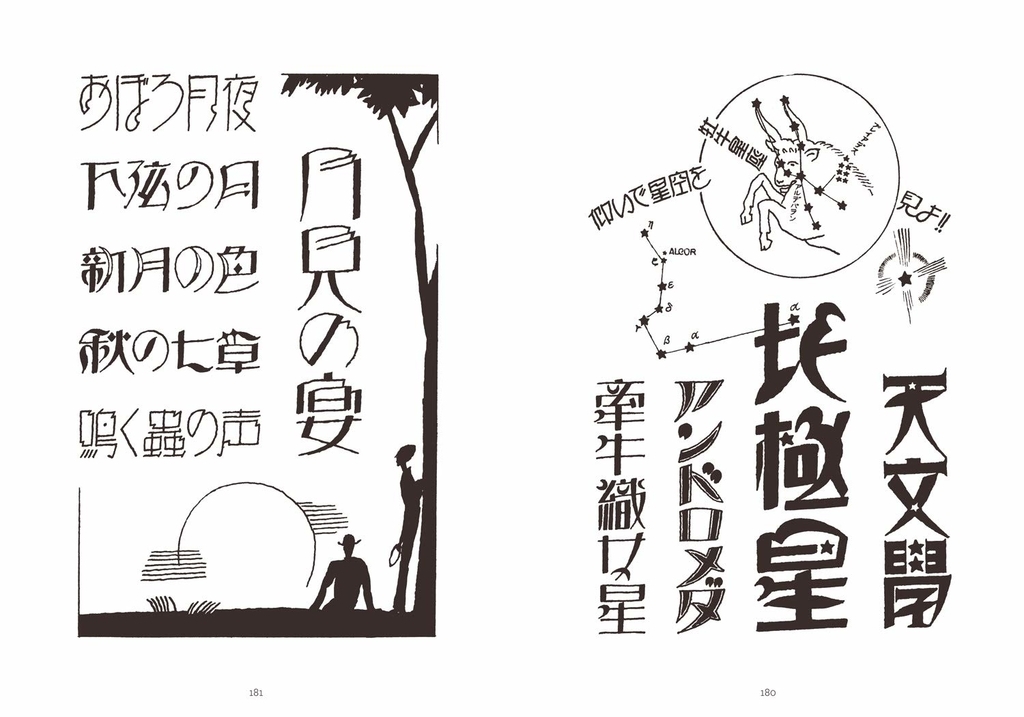
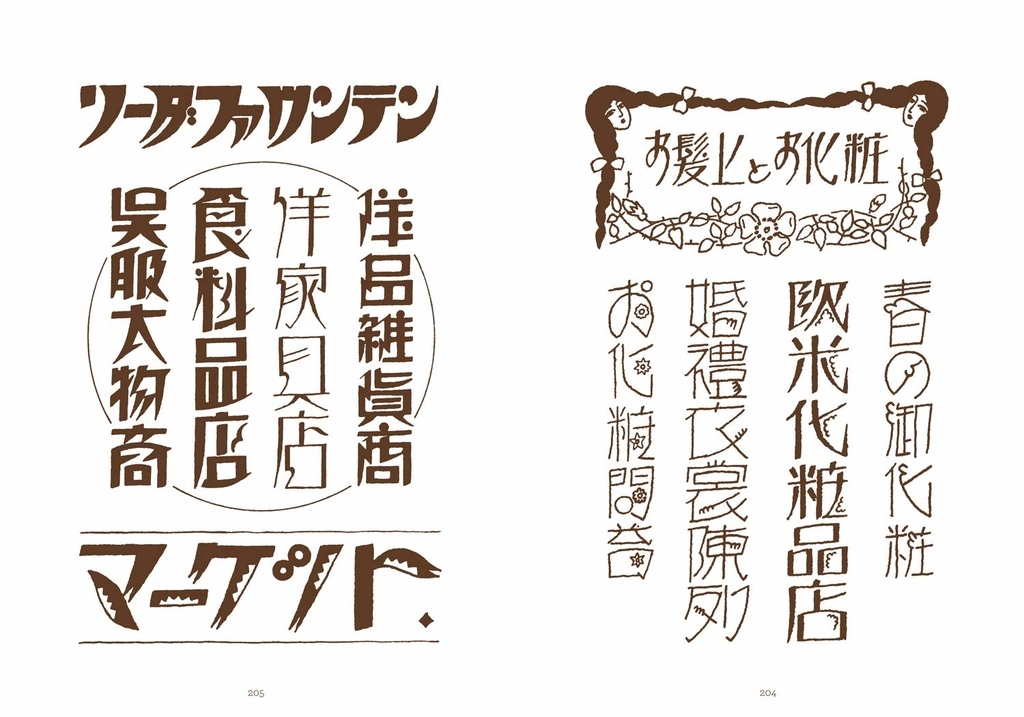
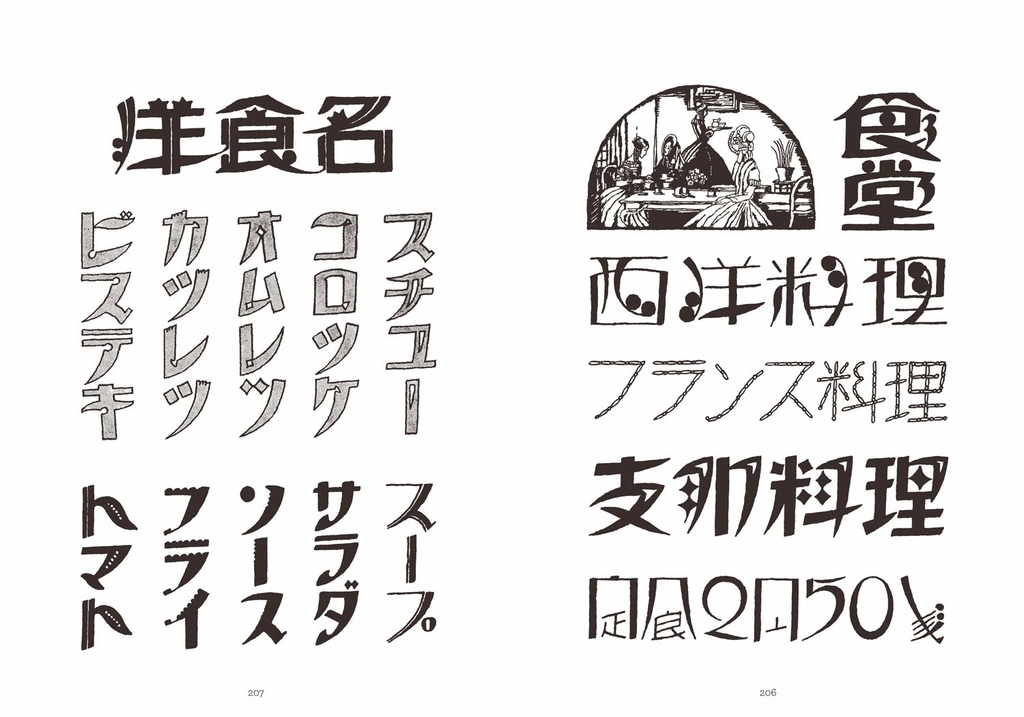
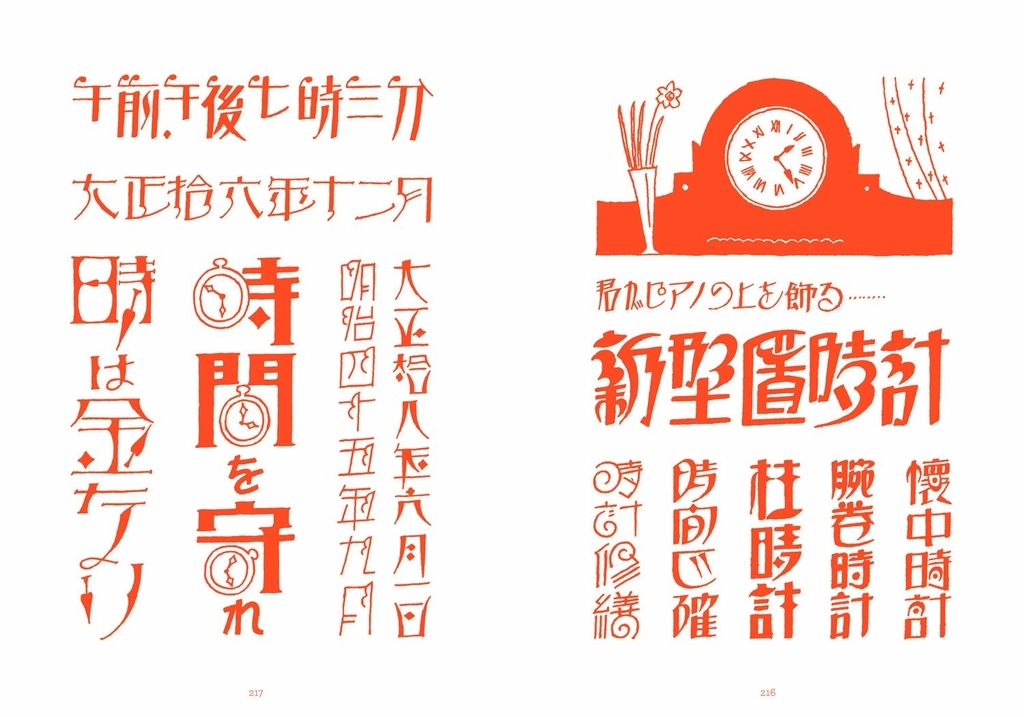
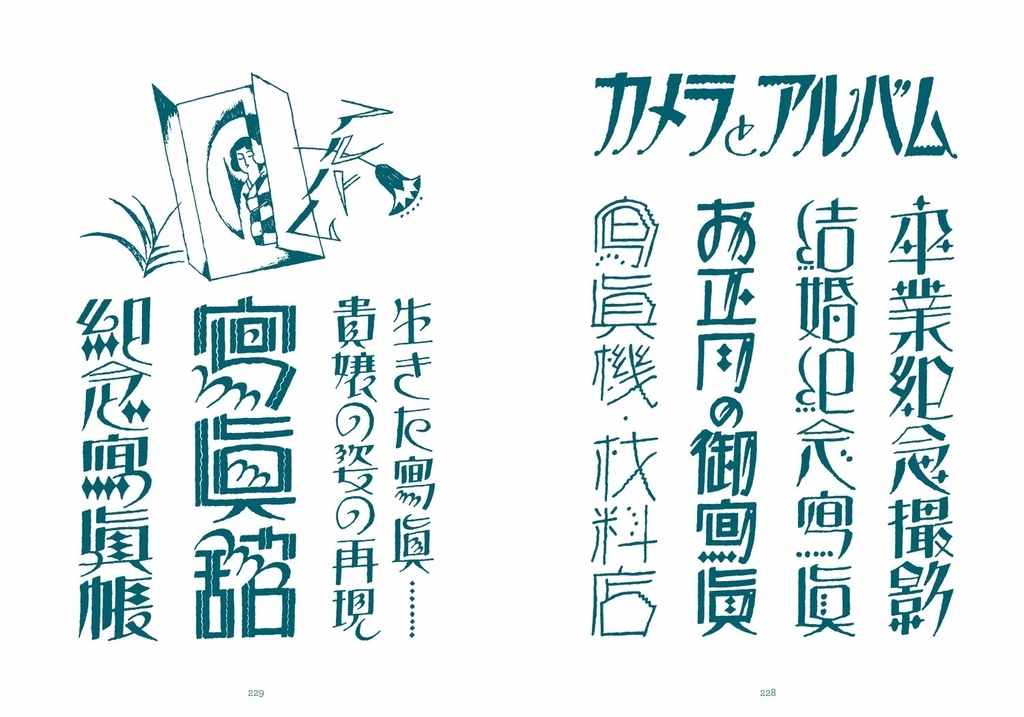
嗚呼、愉しき哉 図案文字の世界。
紳士、淑女の創作活動に、、、。
大正時代のタイポグラフィ名著、待望の復刻。
デザイナー、イラストレーター、フォント好きのためのデザイン資料集です。
本書は、藤原太一編著『図案化せる実用文字』(大正十四年発行)、『絵を配した図案文字』(大正十五年発行)の新装合本復刻版です。
本書掲載の図案文字や図版を、さまざまなデザインやタイトル文字の創作のヒントとしてご活用下さい。
藤原太一著書による「図案化せる実用文字」から着想を得た書体「ロマン雪」
ダイナフォント「ロマン雪」は、藤原太一著書による「図案化せる実用文字」から着想を得て、図中の婦人の華麗な装いや愛らしいスタイルをヒントにして開発された書体。
ロマン雪
1925年の藤原太一著書による『図案化せる実用文字』から着想を得て、図中の婦人の華麗な装いや愛らしいスタイルをヒントにして、大正末期から昭和初期にかけての古典ロマンの雰囲気を再現した書体。ひし形など独特の字形が大きなインパクトを与える事から、ロゴやPOPなどで大きく活用できる。